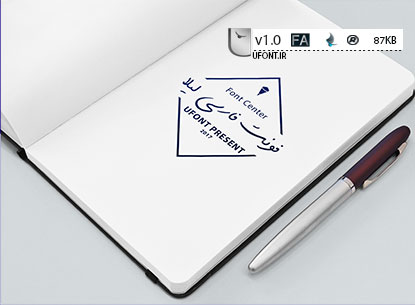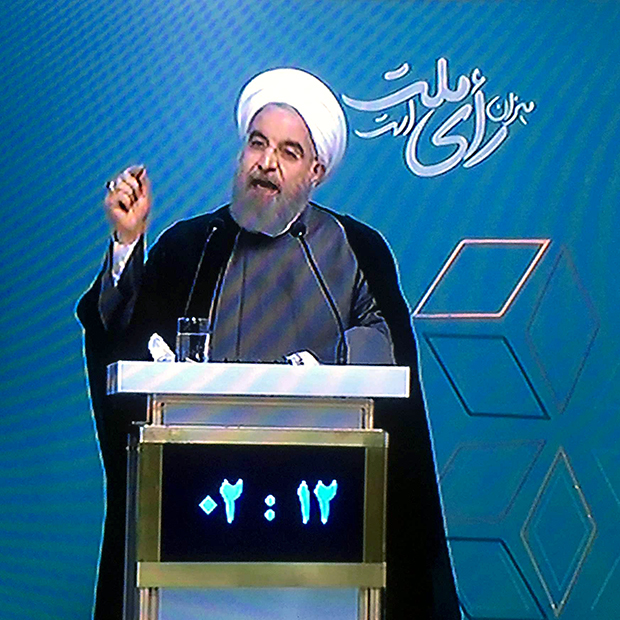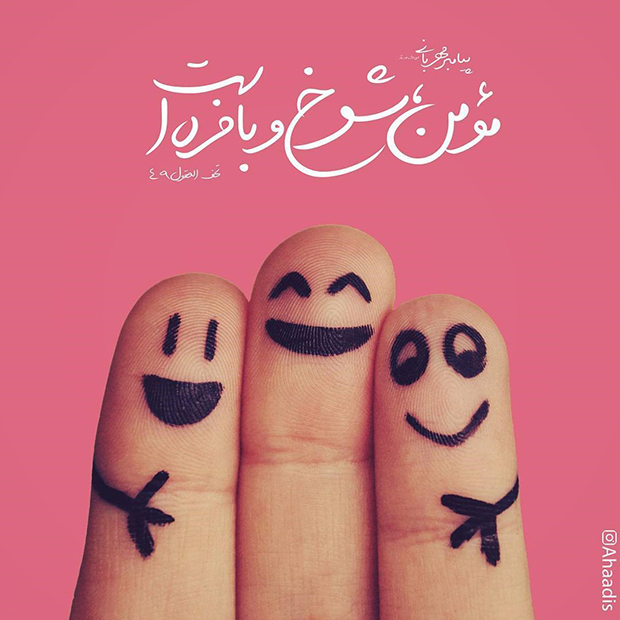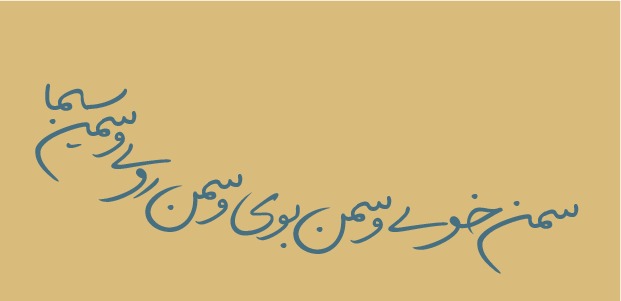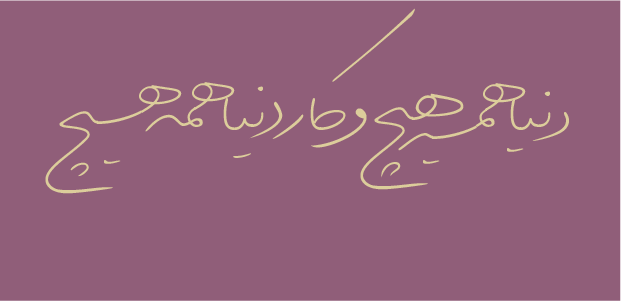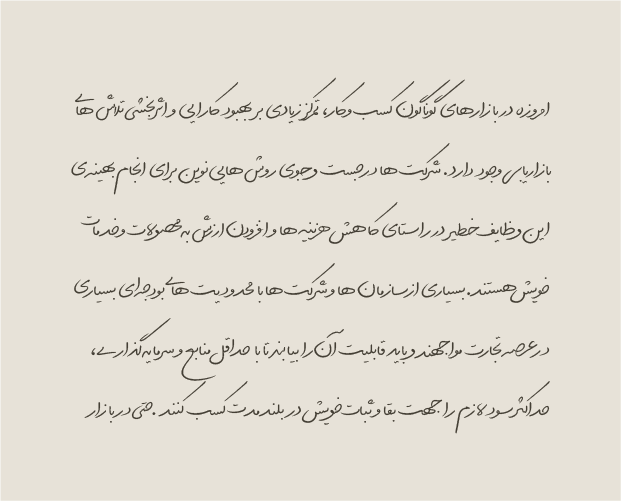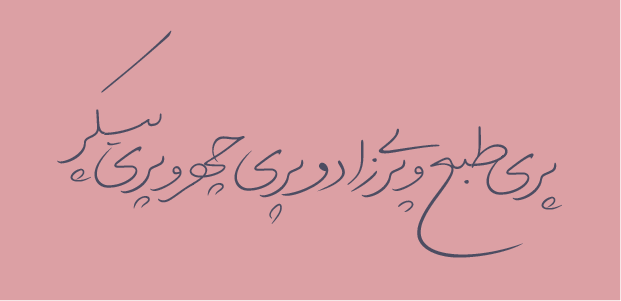
فونت دستنویس لیلا
فونت دستنویس لیلا ، فونتی بسیار زیبا و ساختاری حرفه ای ، این فونت در دسته فونت های دست نویس و جدید فارسی می باشد که مطمئنا نیاز هر گرافیست است ، این دست فونت های برای طرح های تایپوگرافی هم نیز استفاده می شوند و اساسا یک طراحی می بایست اینگونه فونت ها را در آرشیو خود داشته باشد 🙂
فونت دستنویس لیلا
فونت های دست نویسی زیادی از یوفونت منتشر شده است اما این فونت خیلی طبیعی تر از سایر نسخه ها می باشد و هم چنین جدید و گرافیکی است و ساختاری یک پارچه و زیبا دارد
خانوادهی قلم (فونت) لیلا بر پایهی دستخط خواهرم طراحی شده و تلاش بر این بوده تا با بررسی و الگوبرداری از جزوهها و نوشتههای وی، حرکت سریع دست، تغییرات ضخامت خط و حرکتهای خودکار بازنمایی شده تا نوشته مصنوعی بهنظر نرسد. همچنین امکان استفاده از مرکبات و جایگزینهای متنوع باعث جلوگیری از تکرار زیاد فرمها میشود و حس بداهگی نوشتن را القا میکند. طراحی لیلا سال ۱۳۸۷ آغاز شد و وزن Regular آن در سال ۱۳۹۳ پایان یافت، لیلای Light و Bold در سال ۹۵ طراحی و اجرا شد